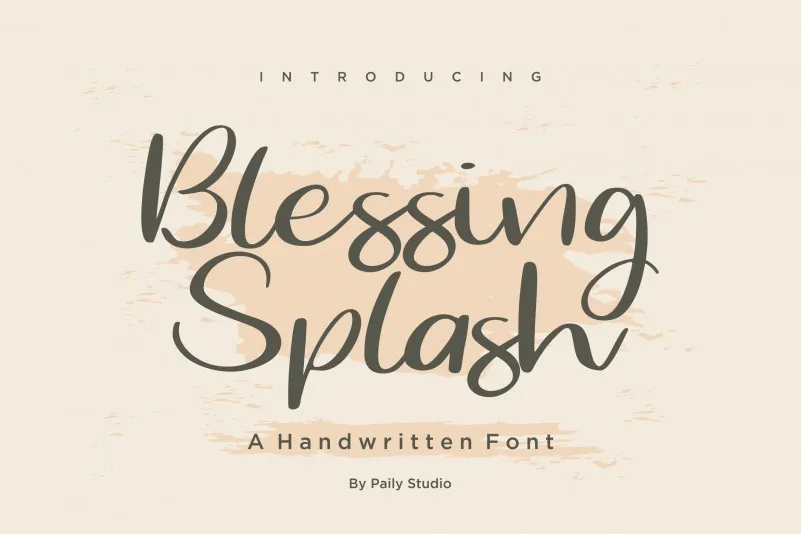
Blessing Splash Font – Download Grátis
A fonte ‘Blessing Splash Font’ é uma elegante escolha para designers que buscam expressar sentimentos suaves e emotivos em seus projetos digitais. Ela foi criada pelo Paily Studio, um estúdio conhecido por produzir fonts com estilo autêntico de escrita. ‘Blessing Splash Font’ é uma fonte gravitacional perfeita para designers que procuram um touch delicado e natural em suas criações. A designadora do Paily Studio tem uma habilidade única de criar texturas de escrever com personalidade, tornando a ‘Blessing Splash Font’ uma opção irresistível para quem quer adicionar um toque especial à sua arte digital. Suas linhas delicadas e textura são perfeitas para uso em design de casamento, logotipos e cartões de nome, entre outros projetos. Além disso, a fonte é ideal para a criação de postagens nas redes sociais, promovendo um estilo único e autêntico. A ‘Blessing Splash Font’ combina uma seriedade discreta com uma sensibilidade emocional natural, oferecendo aos designers a oportunidade de trazer vida e personalidade para seus projetos. Esta fonte é uma escolha perfeita tanto para aqueles que buscam criar um ar pessoal em suas criações quanto para aqueles que procuram um estilo único e envolvente, capaz de transmitir sentimentos através do design digital.